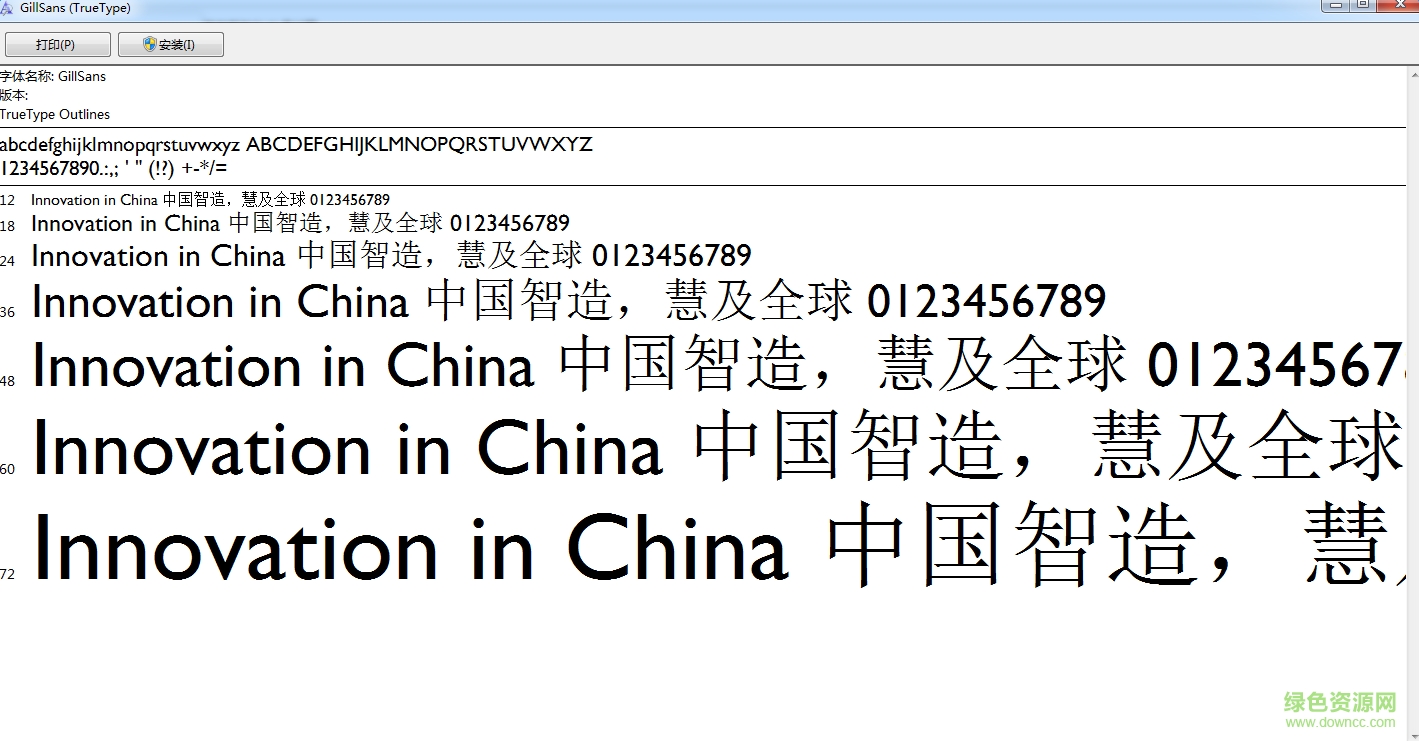
gill sans字體是一款古典英文體,字形精致優(yōu)美,細(xì)節(jié)處理出色,可應(yīng)用于影視、廣告、ppt等眾多領(lǐng)域,喜歡該字體的小伙伴快來綠色資源網(wǎng)下載吧!
古典體或稱為人文主義體,常見的古典體有Johnston、Frutiger、Gill Sans、Lucida、Myriad、Optima、Segoe UI、Tahoma、Trebuchet MS、Verdana等。這些字體是無襯線字體中最具書法特色的,有更強(qiáng)烈的筆畫粗細(xì)變化和可讀性。